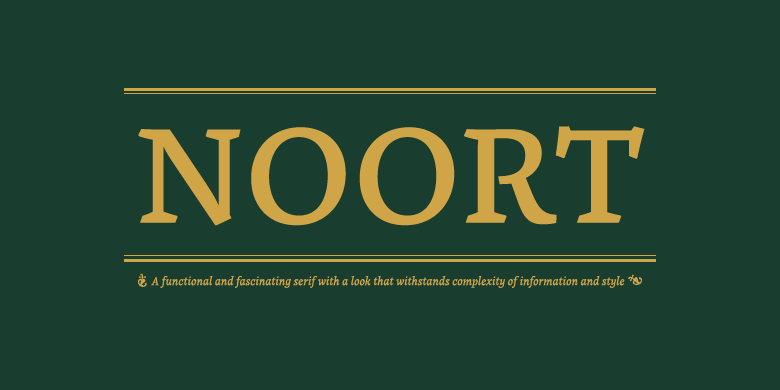
Noort
Noort,这款字体结构工整、笔画清晰,兼顾美观与易读性,适用于标题、正文、海报、包装、LOGO 等多种场景。字形优雅稳定,风格百搭耐看,适配日常排版与创意设计,让文字呈现更舒适、更具质感。Noort一笔一画,皆是细节,以均衡的比例、流畅的线条打造舒适视觉体验,字形端正大气,风格简约现代。无论是商业设计、品牌宣传还是日常排版,都能轻松驾驭,让文字更有格调与力量。Noort字体下载。
字体品牌: TypeTogether 设计师:JuanBruce 字体分类:衬线体 字体属性:外文 字符集:Unicode 发布时间: 2018
A functional and fascinating serif with a look that withstands complexity of information and style, by Juan Bruce.